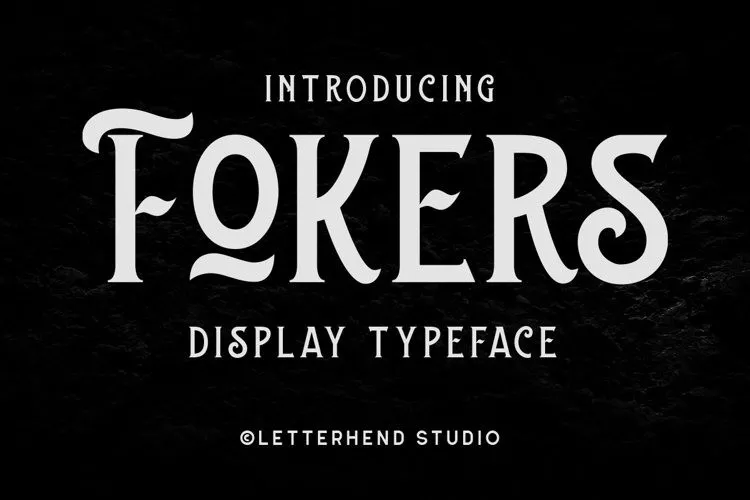
Fokers Font – Fonte Grátis
Fokers Font
A Fokers Font é uma criação única para tipos de mídia de destaque, desenvolvida por Letterhend Studio. Ela oferece um visual classe e luxuoso perfeito para quem procura um tipoface para headlines, logotipos, roupas, convites, marcações, embalagens, propaganda etc. Esta fonte inclui letras maiúsculas e minúsculas, pontuação, símbolos, números, set alternativo estilizado, ligaduras e suporta várias línguas. A Fokers Font é uma excelente opção para qualquer projeto que exija um tipo de mídia chamativa e impecavelmente elegante. Composto por letras maiúsculas e minúsculas, a Fokers Font oferece flexibilidade para personalizar seu design e combinar com vários estilos. Ela é perfeita para dar uma sensação única a qualquer projeto que seja apresentado em público. Quebre as barreiras da monotonia e transforme sua identidade visual de um simples texto padrão em algo que impressionará seus clientes com estilo e sofisticação. A Fokers Font está aqui para tornar o seu próximo projeto ainda mais impactante.